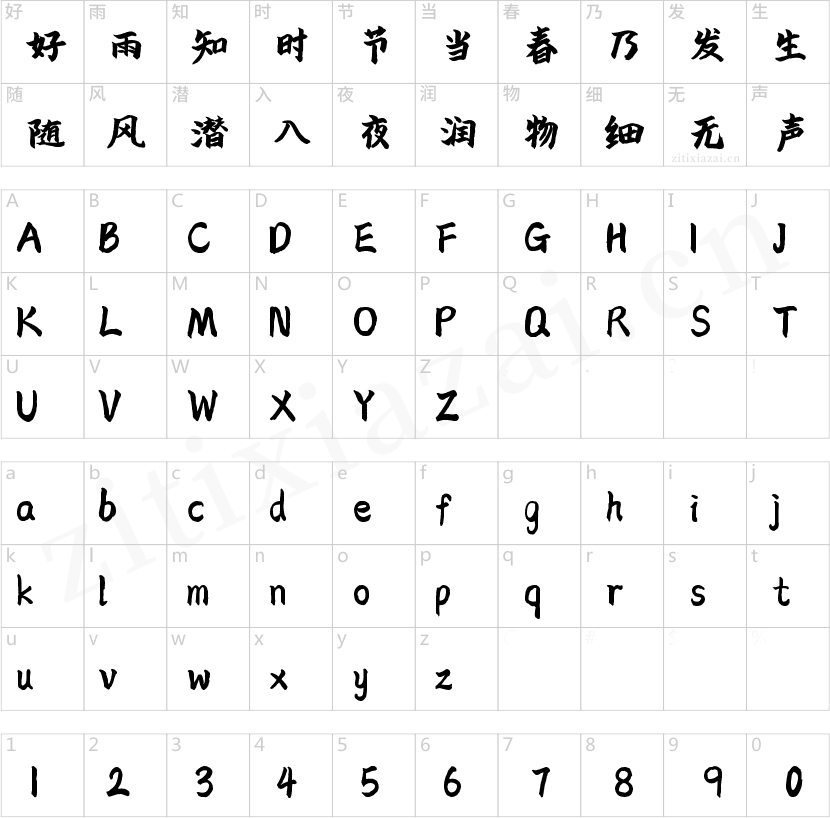
字魂121号-山海手书
字魂121号-山海手书,这款字体结构工整、笔画清晰,兼顾美观与易读性,适用于标题、正文、海报、包装、LOGO 等多种场景。字形优雅稳定,风格百搭耐看,适配日常排版与创意设计,让文字呈现更舒适、更具质感。字魂121号-山海手书一笔一画,皆是细节,以均衡的比例、流畅的线条打造舒适视觉体验,字形端正大气,风格简约现代。无论是商业设计、品牌宣传还是日常排版,都能轻松驾驭,让文字更有格调与力量。字魂121号-山海手书字体下载。
字魂字体字小魂山海手书字体是由字魂创意字库设计并生产的一款可商用的字体,被收录于字小魂系列。该字体支持GB-2312标准,包含6763个中文、字母、符号和数字,字体类型偏向毛笔书法,具有力量、豪放、活泼、中国风、帅气的风格,在市面上广泛用于晚会年会、海报企宣、媒体&H5等场景。